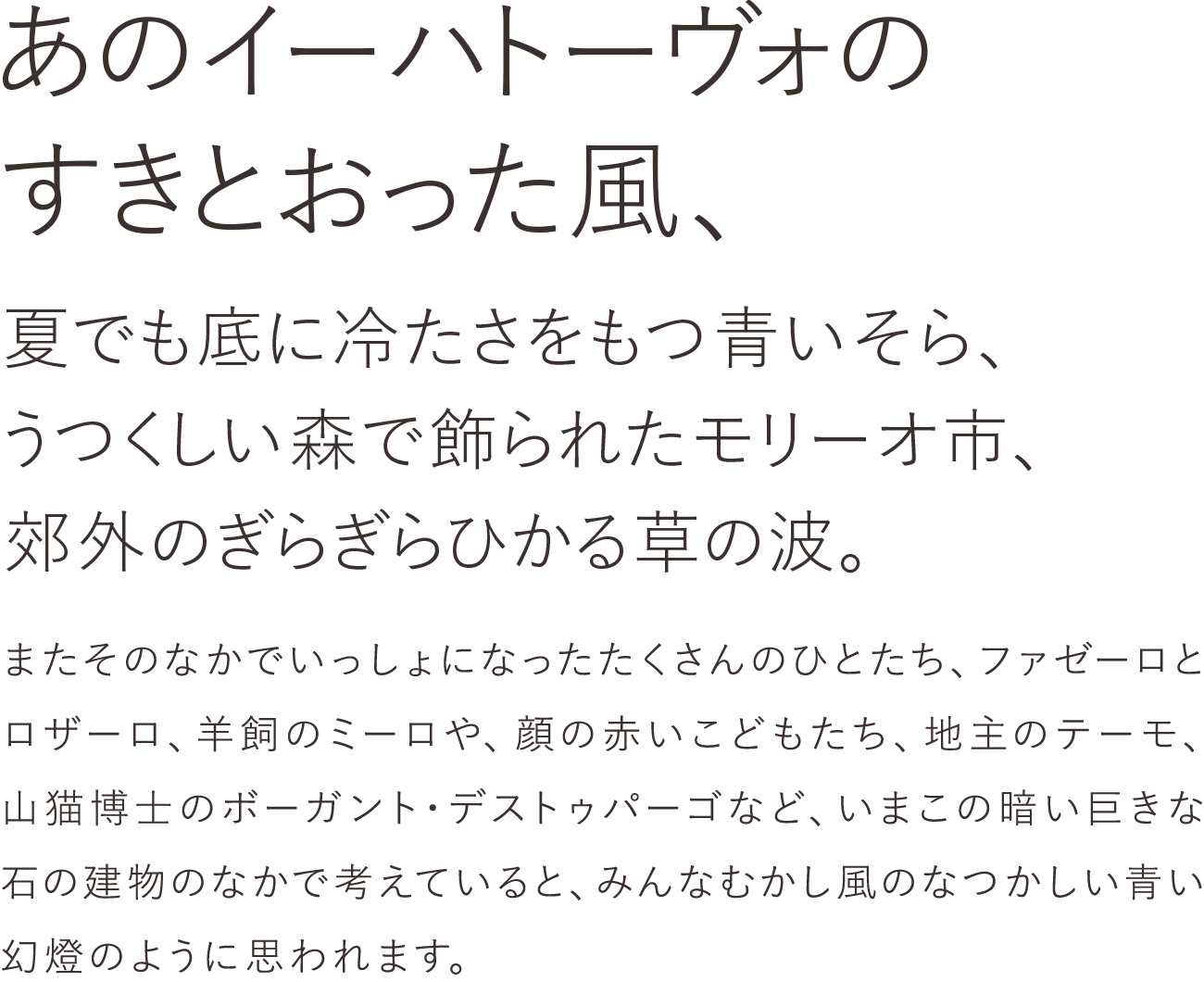
游ゴシック体 R
「游明朝体」との組み合わせを想定し制作された、スタンダードなゴシック体フォント。こぶりなかなとややふところの締まった漢字が文字間にゆとりを生み、サイズや文章の長さ問わず読みやすい設計になっています。誠実な印象と7ウエイト展開で、デザインからビジネスシーンまで幅広い用途に対応可能!